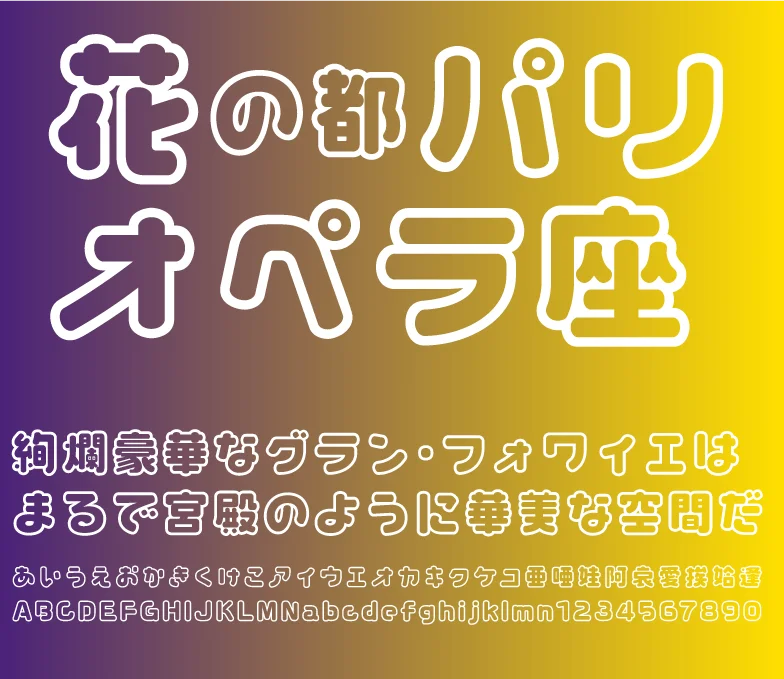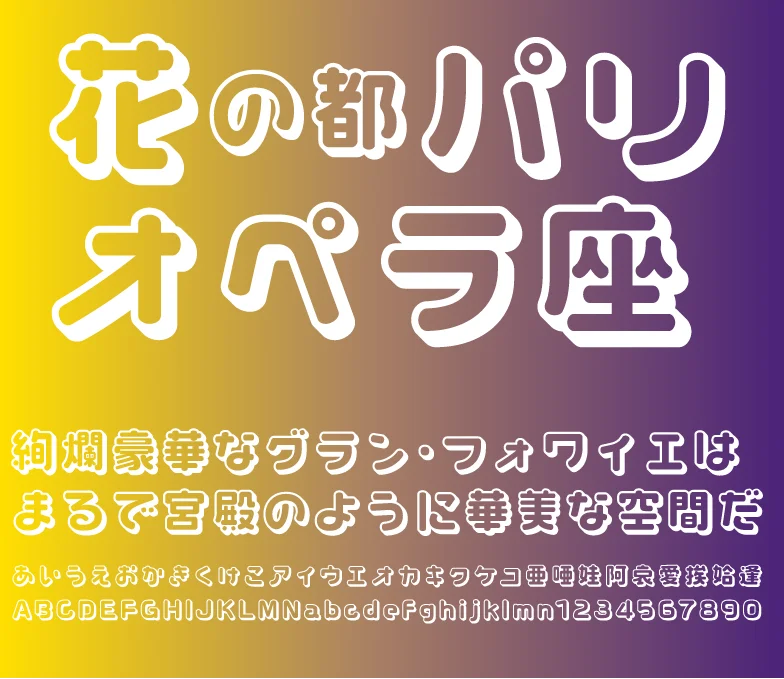
メガ丸-popの特徴
「メガ丸-pop」は、「メガ丸」のデザインをベースに生まれた装飾書体です。文字の輪郭線のみを強調したデザインの「メガ丸-pop-FutoLine」と、文字の背後に影を落とし立体的なデザインに見せる効果を持つ「メガ丸-pop-Shadow」があります。
●FutoLine
メガ丸-pop-FutoLine
●Shadow
メガ丸-pop-Shadow